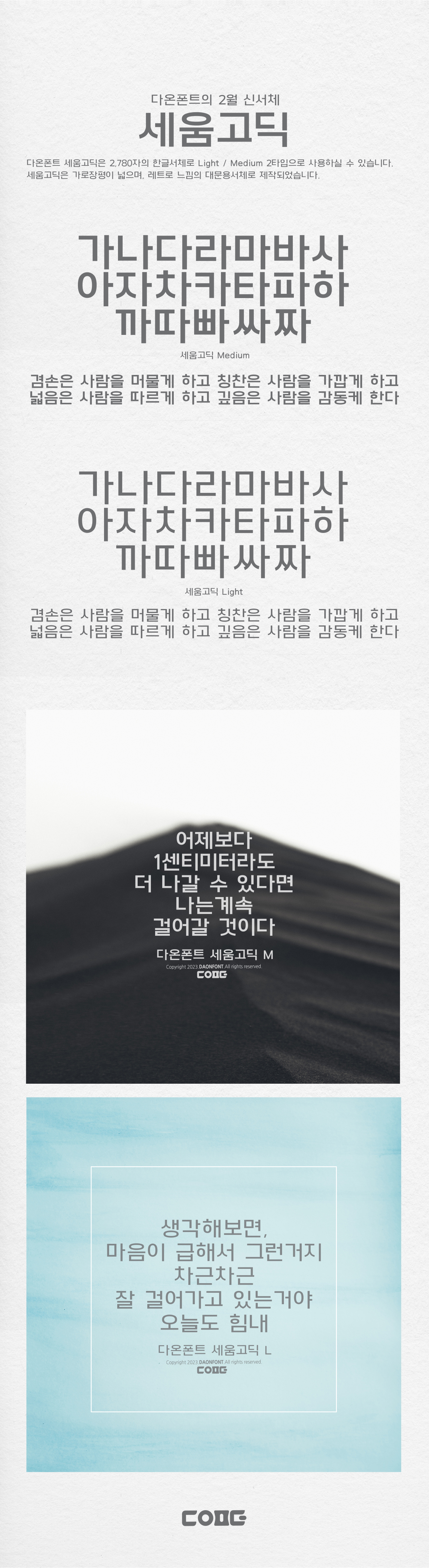
2월 신서체 다온폰트 "세움고딕" 출시
2월 신서체인 다온폰트 "세움고딕"이 업데이트 되었습니다.
다온폰트 "세움고딕"은 가로장평이 넓으며, 레트로 느낌의 대문서체로 제작이 되었습니다.
한글 2780자로 구성되어 있으며, 자소굵기에 따라 Medium/Light 2종으로 사용하실 수 있습니다.